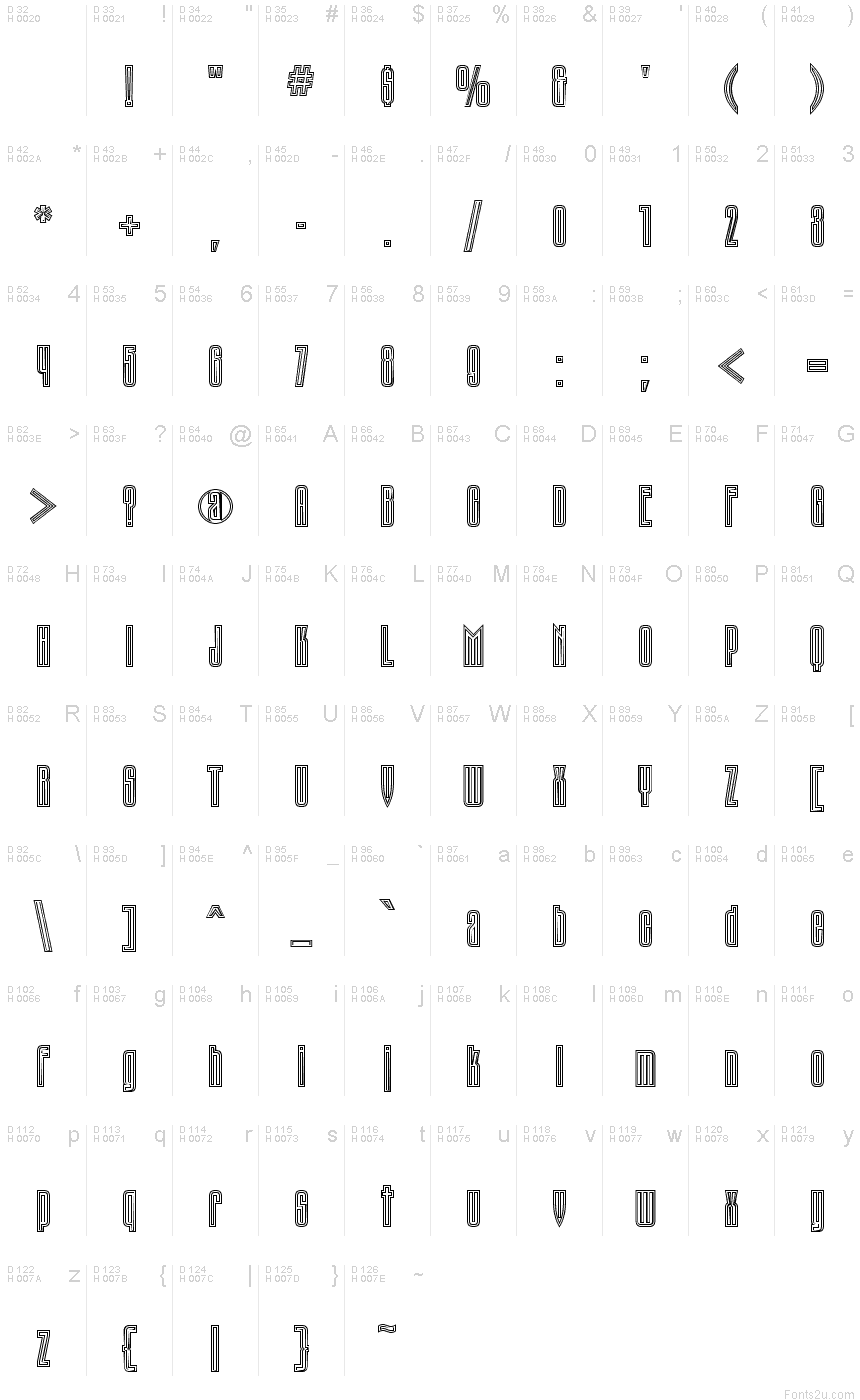
NK44 — это бесплатный кириллический акцидентный шрифт со строгим, позднемодернистским характером. Буквы построены как высокие прямоугольные рамки из узких параллельных линий, что придает дизайну архитектурный вид, напоминающий одновременно неоновые вывески и разлинованную бумагу.
Благодаря этому шрифт органично вписывается в заголовки плакатов, обложки пластинок, титры, событийную графику и дерзкий брендинг, где короткие слова подчеркивают паттерн. Будучи бесплатным, он также отлично подойдет для зинов, клубных флаеров, редакционных врезок и монограмм, особенно если вы хотите, чтобы вертикальный ритм и полосатая фактура букв брали на себя основную визуальную нагрузку.